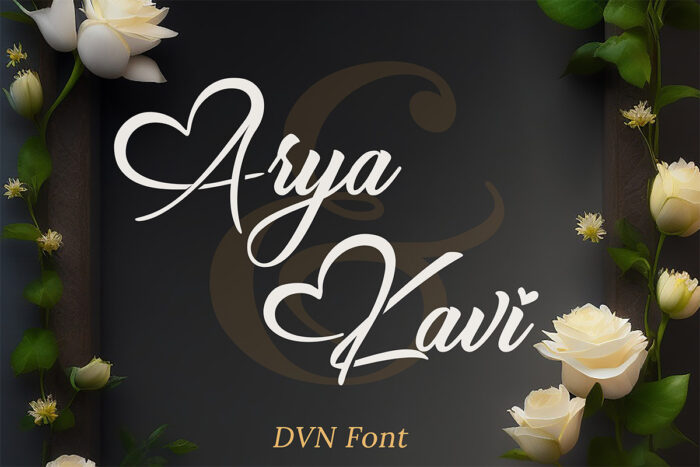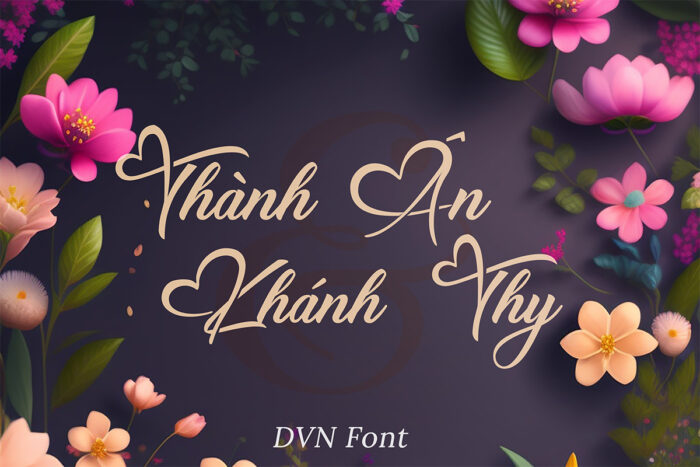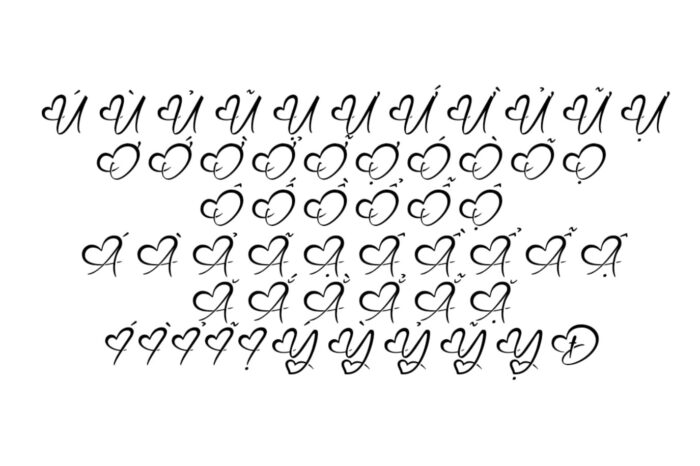
DVN Hearth Việt hóa – Font chữ trái tim cách điệu tuyệt đẹp
Font chữ DVN Hearth có kiểu dáng độc đáo, kết hợp giữa sự hiện đại và nét cổ điển. Các đường nét của DVN Hearth mềm mại và thanh thoát, thể hiện rõ ràng qua các chữ cái được thiết kế một cách tinh tế. Điểm nổi bật của font chữ này là những đường cong mềm mại và độ dày của nét chữ không đồng đều, tạo cảm giác bay bổng và lãng mạn. Mỗi ký tự đều có sự chênh lệch nhỏ về kích thước và khoảng cách, mang lại cảm giác tự nhiên và nghệ thuật.
Ứng dụng của font chữ DVN Hearth rất đa dạng, phù hợp cho các thiết kế liên quan đến tình yêu, sự lãng mạn như thiệp chúc mừng, thiệp cưới, các bài thơ, và thiết kế liên quan đến ngày lễ tình nhân. Ngoài ra, DVN Hearth cũng phù hợp cho các thương hiệu muốn truyền tải sự nhẹ nhàng, nữ tính và tinh tế trong thông điệp của mình. Font chữ này chắc chắn sẽ làm nổi bật và mang lại sự ấn tượng đặc biệt cho các dự án thiết kế.